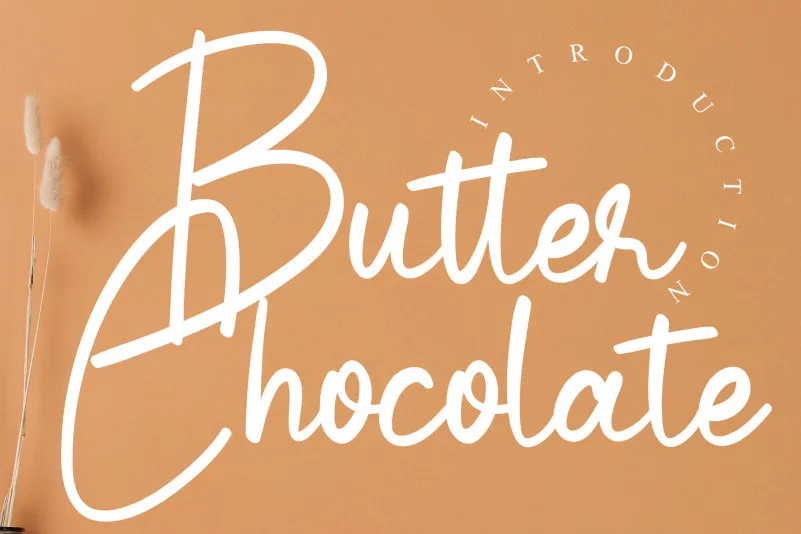
A ‘Butter Chocolate Script Font’ é uma criação única que carrega consigo a delicadeza do chocolate branco com sua textura macia e suave, enquanto mantém um charme elegante característico dos gabinetes de letras escritas à mão. Esta fonte não apenas tornará suas publicações mais atraentes, mas também proporcionará uma experiência única ao seu público-alvo, destacando-se em qualquer projeto onde ela seja aplicada. Ideal para designers que desejam dar um toque personalizado e sofisticado aos seus materiais digitais, esta fonte é perfeita para aqueles buscando algo mais além do comum. Com sua escrita cuidadosamente elaborada à mão, você consegue transmitir uma emoção única através de cada letra, criando textos que não apenas são legíveis, mas também envolvem e agradam aos olhos. A ‘Butter Chocolate Script Font’ é o resultado do amor pelo design e por criar algo especial, destinado a entusiasmar designers apaixonados pela mistura única entre elegância e delicadeza.